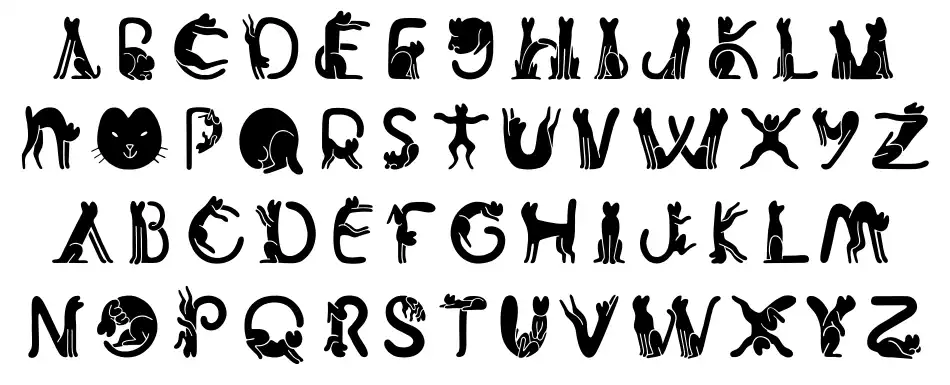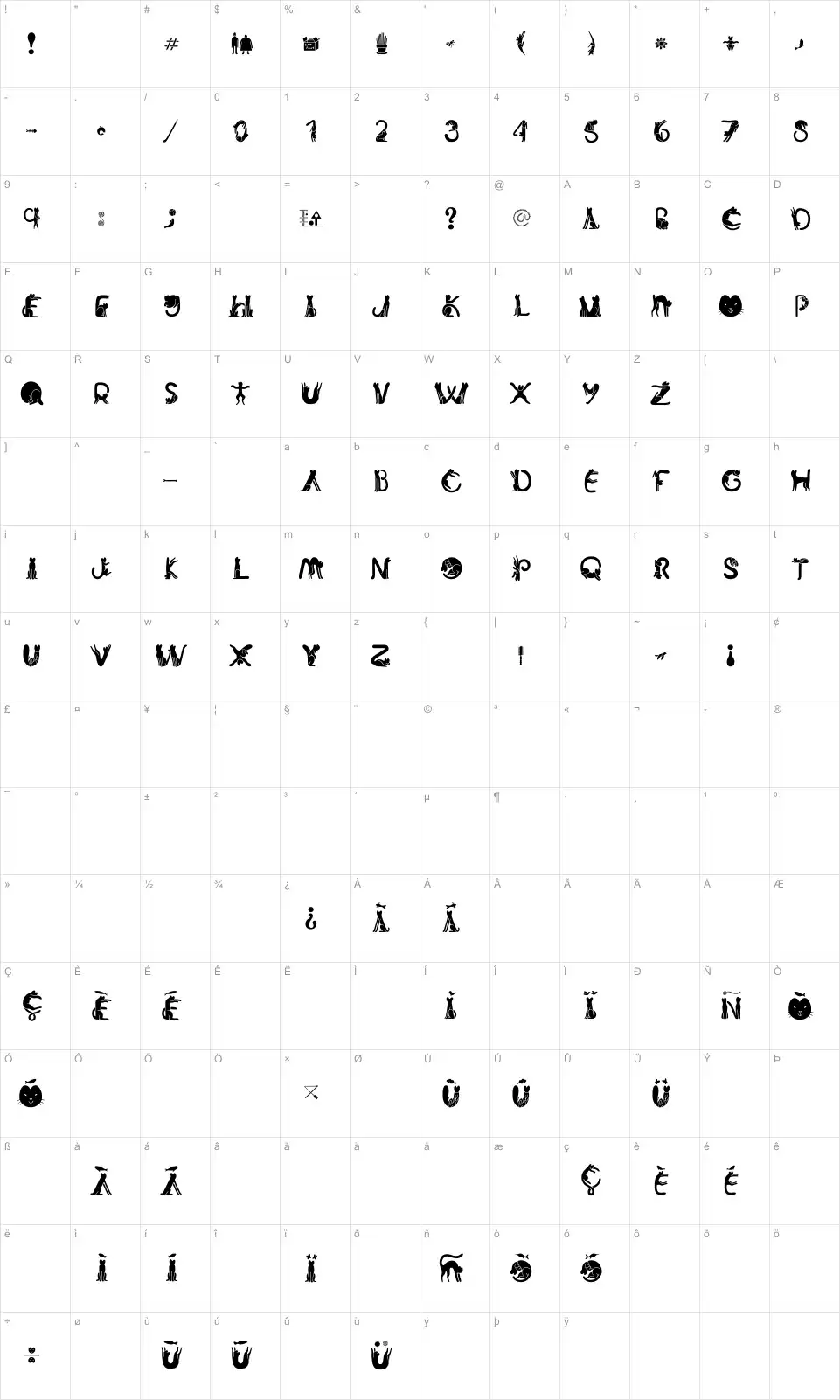
A fonte ‘Cat Font’, criada pelo designer Jaime Vicente, é uma escolha perfeita para qualquer projeto que busque um ar sofisticado e divertido ao mesmo tempo. Esta fonte caprichada, categorizada como Fancy e Decorative, oferece uma aparição única e irreverente que pode transformar qualquer texto em um verdadeiro espetáculo visual. Licenciada para uso pessoal, a fonte ‘Cat Font’ está disponível em formato TTF, permitindo que você a use em seu projeto sem precisar pagar mais nada além de o seu bom senso. Adicionada ao nosso catálogo em 12 de julho de 2022, a fonte já foi baixada mais de três mil vezes, mostrando a sua popularidade entre criadores de conteúdo e designers. Se você está procurando por uma maneira criativa de personalizar o texto para um projeto ou uma campanha, a ‘Cat Font’ oferece uma oportunidade única. Você pode criar um preview online da sua mensagem personalizada para visualizar como a fonte ficará antes de usá-la. É uma maneira eficaz de garantir que a fonte se adequa perfeitamente ao seu projeto. Sem dúvida, ‘Cat Font’ é a fonte ideal para aqueles que buscam um toque único e divertido em seus trabalhos. Visite o site do designer, http://jaimevicente.com, para mais informações sobre suas outras criações.
Designer: Jaime Vicente